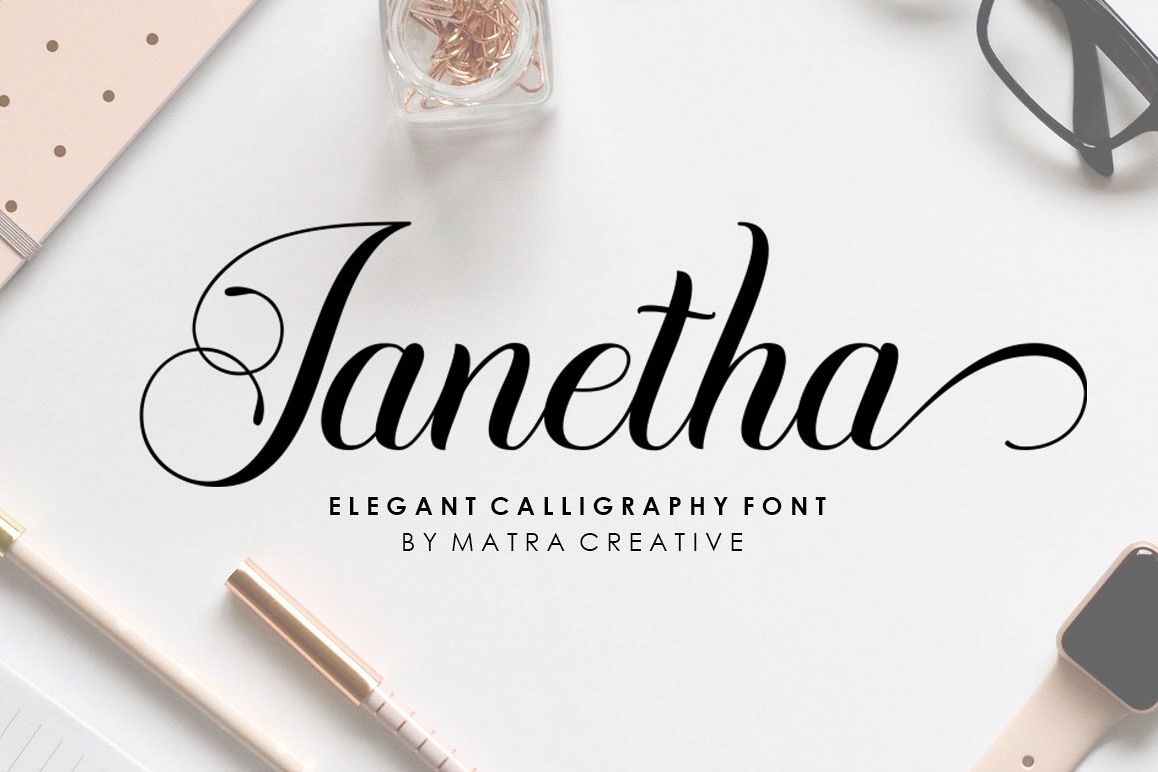
Janetha Script
Janetha Script Font adalah font skrip formal dengan dukungan multibahasa. Sangat ideal untuk undangan pernikahan, majalah, media sosial, menu restoran, kartu ucapan, undangan ulang tahun, header dan banyak lagi.
Font ini dilengkapi dengan satu set lengkap karakter huruf kecil dan huruf besar, berbagai macam tanda baca ligatures, angka dan dan dukungan multibahasa.